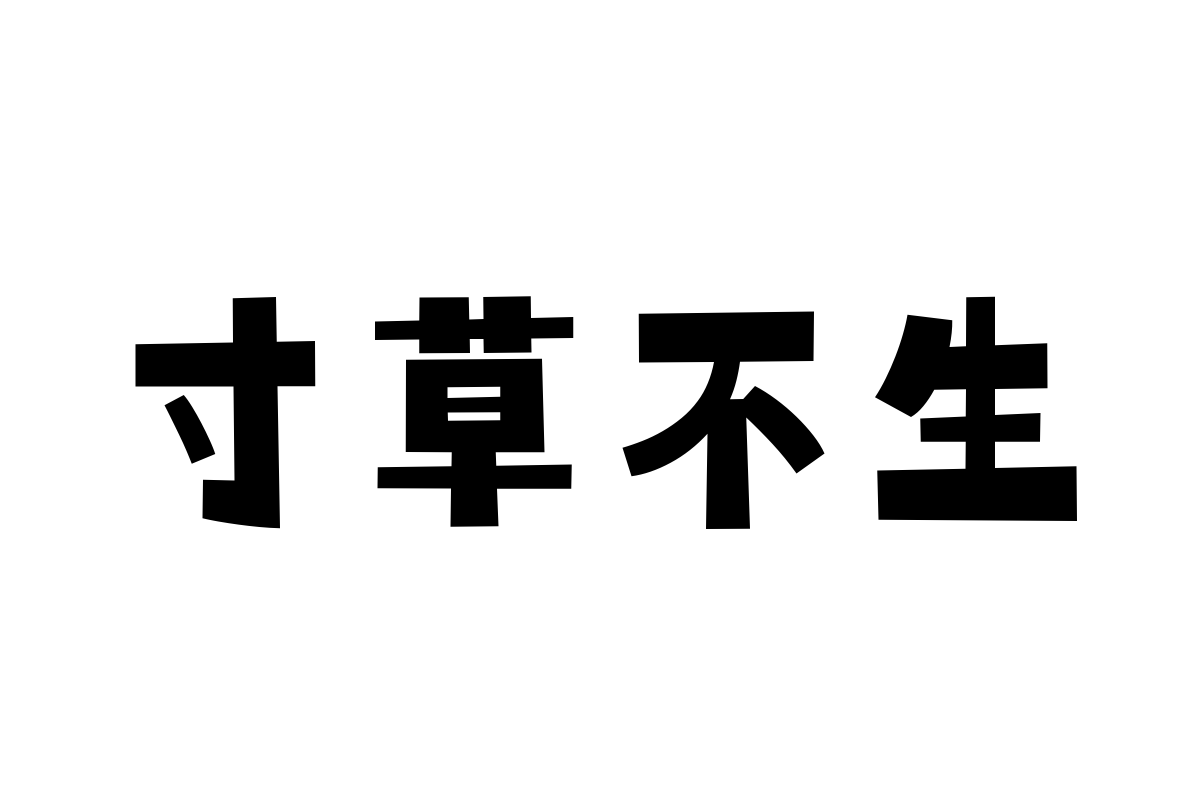
汉仪懒酷酷是一款具有独特风格的中文字体。它采用了现代的设计风格,线条流畅而有力,给人一种简约而时尚的感觉。这款字体的特点是字形结构紧凑,笔画粗细适中,既适合用于标题、正文等需要突出显示的部分,也适合用于广告、杂志等需要吸引眼球的设计。同时,汉仪懒酷酷还注重细节的处理,如字形的圆润度、字距的调整等,使得整体效果更加和谐美观。总的来说,汉仪懒酷酷是一款非常实用的中文字体,无论是在平面设计还是网页设计中都能发挥出色的效果。